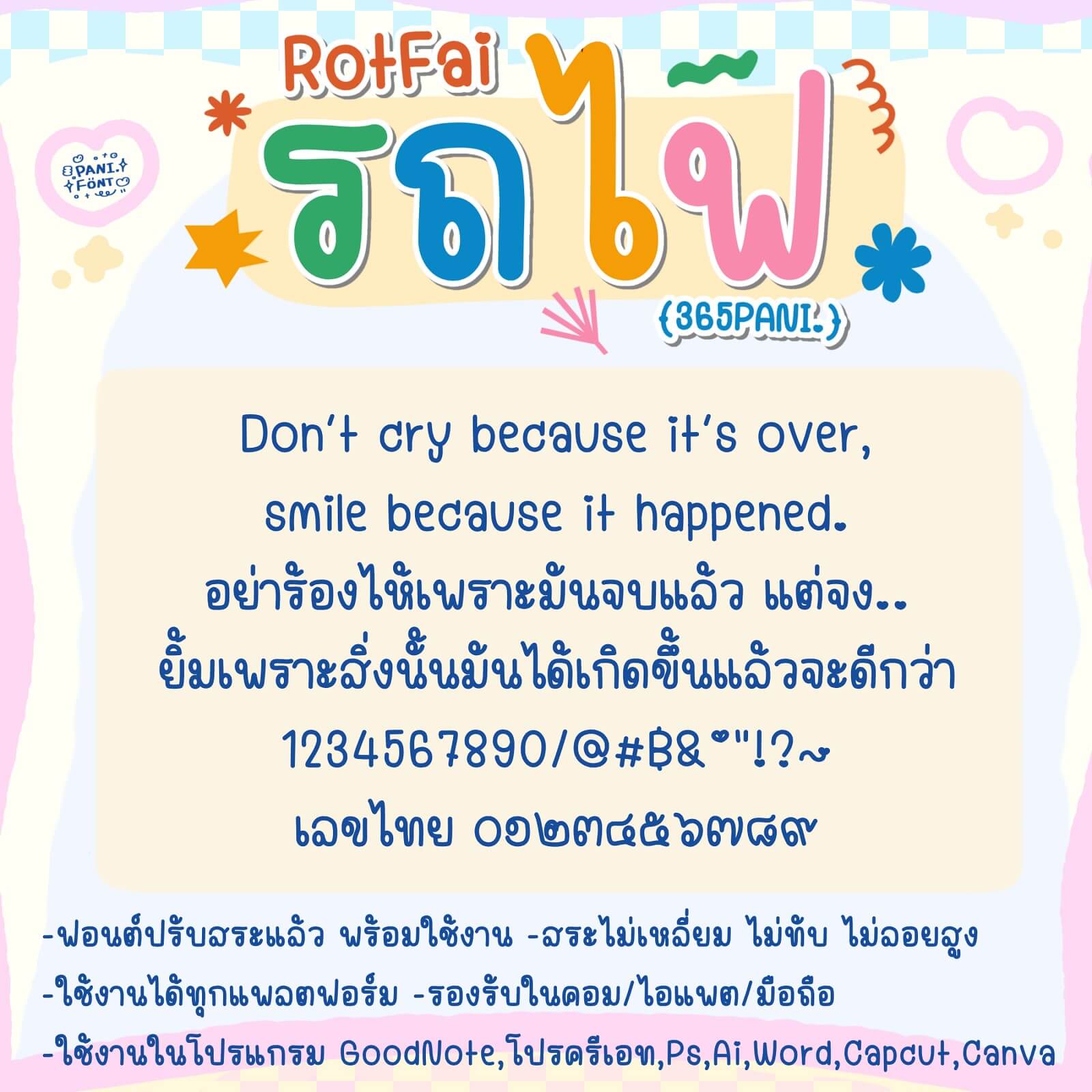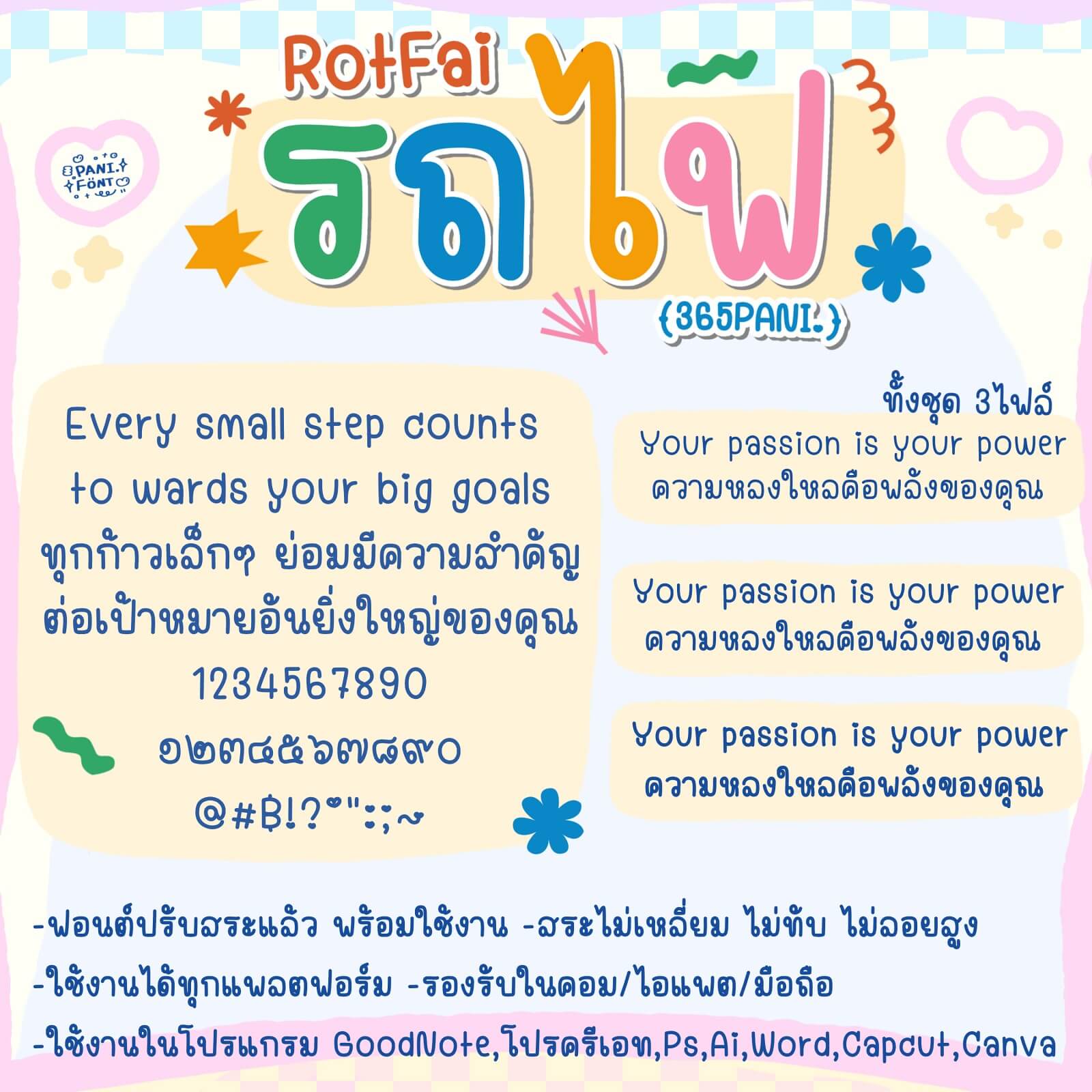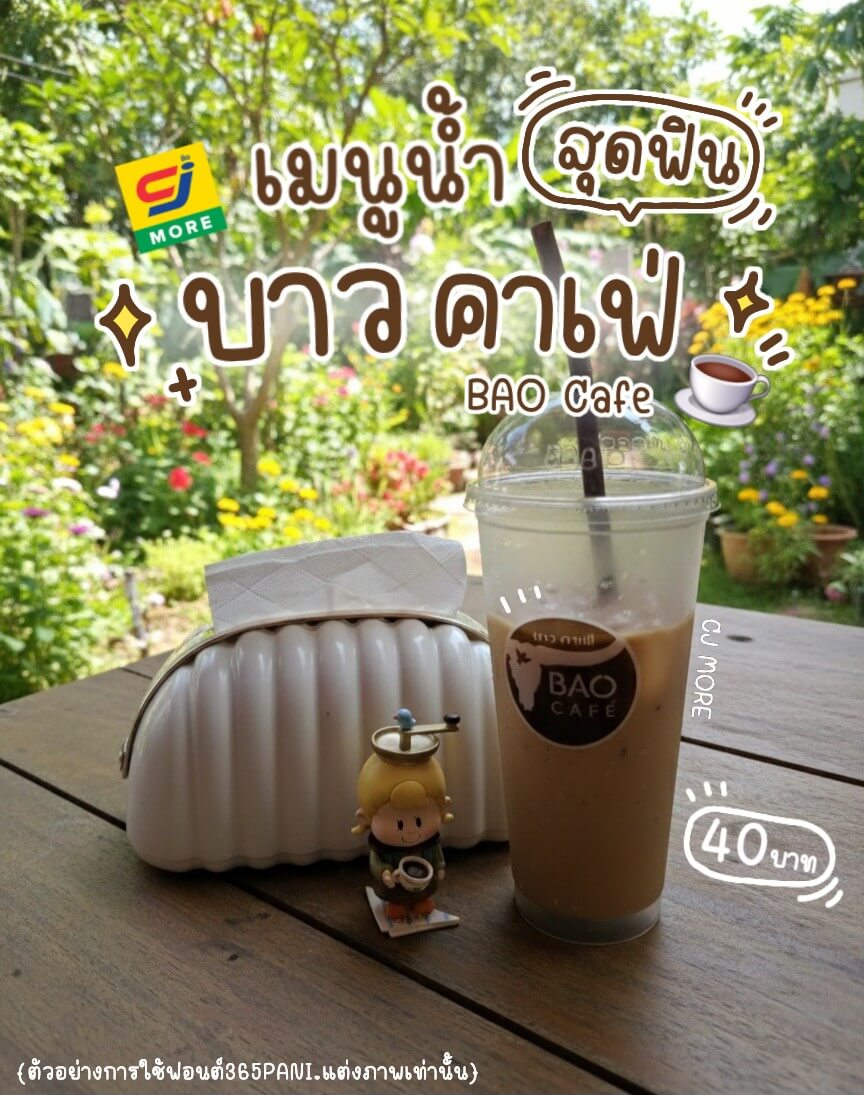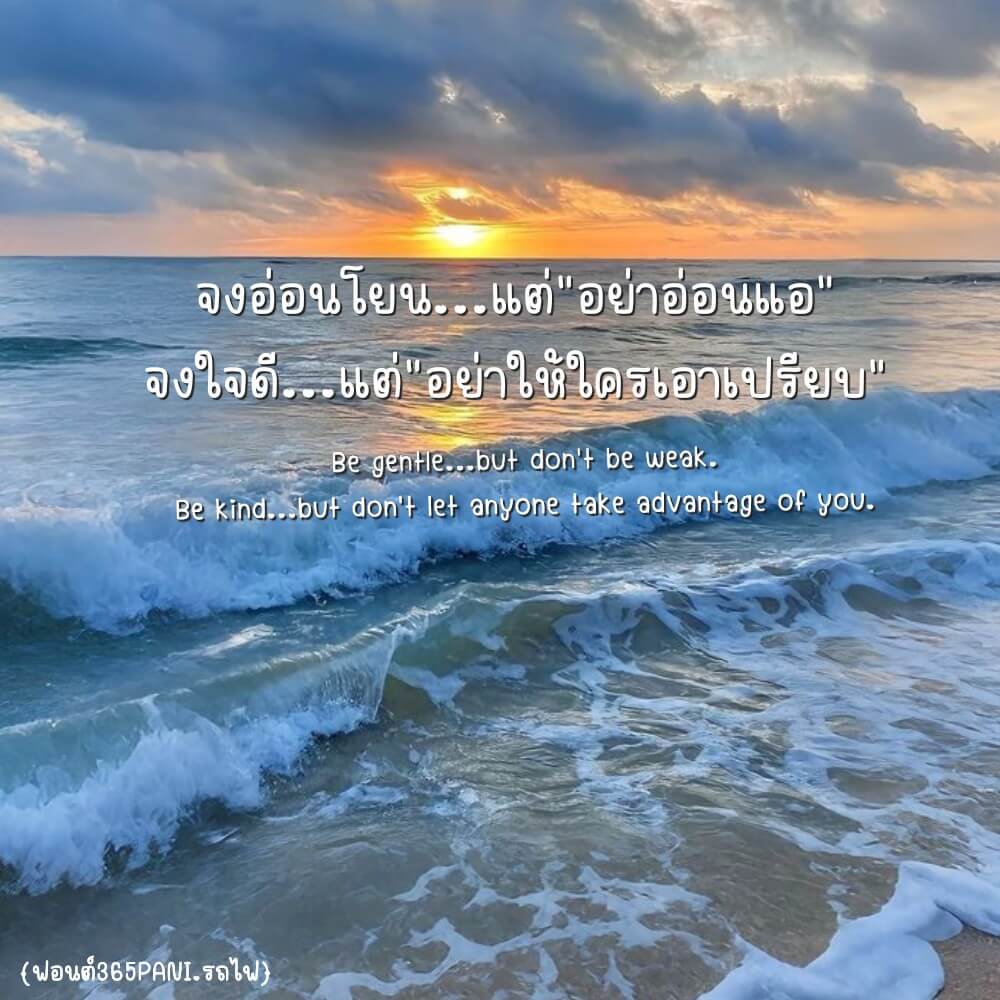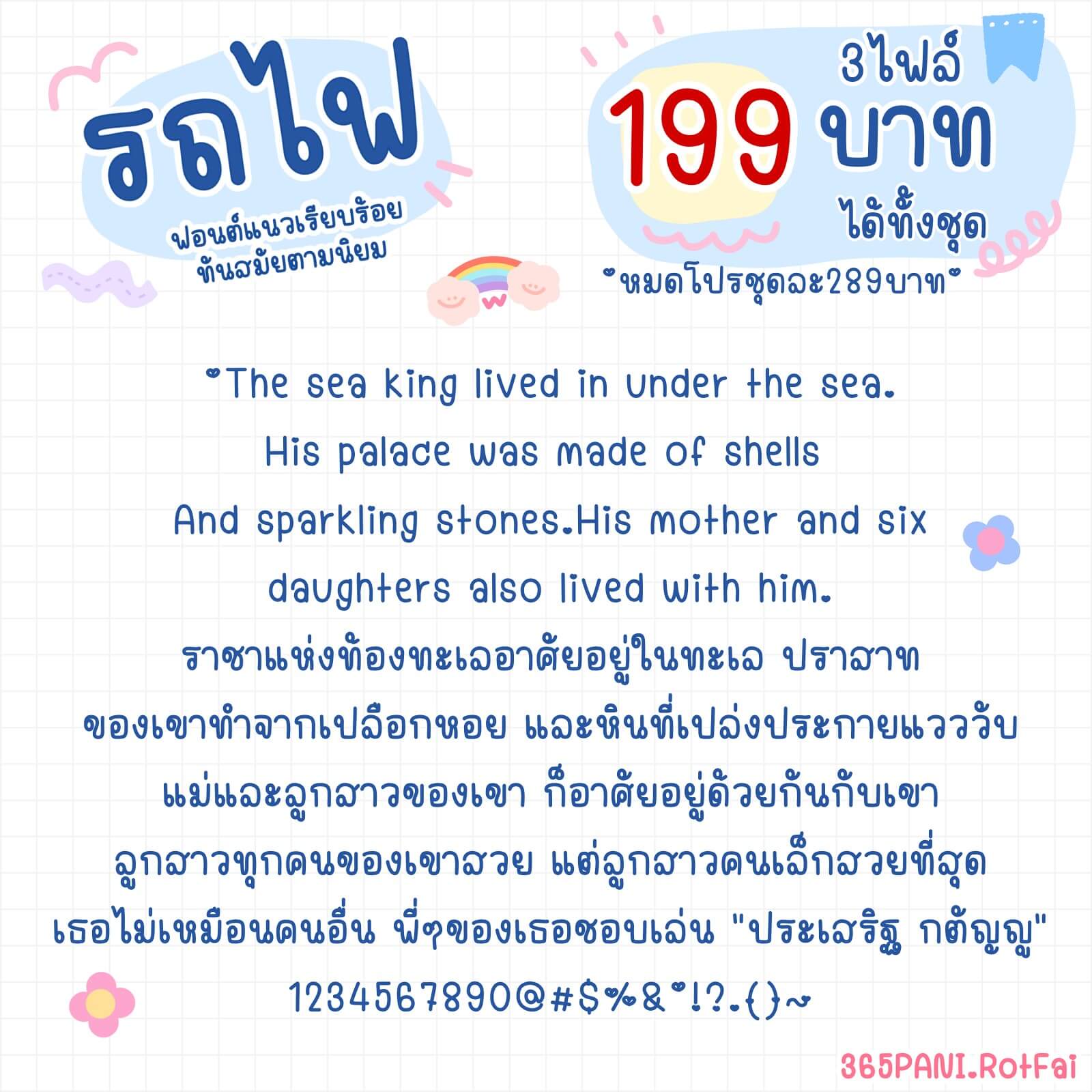
365PANI.รถไฟ
ฟอนต์ 365PANI.รถไฟ – ฟอนต์แนวอ่านง่าย เรียบร้อย ตัวขนาดกำลังดี ใช้แล้วมีความอบอุ่น ชัดเจน เหมาะกับชิ้นงานหลากหลาย จดรายละเอียด ทั้งแต่งภาพ แต่งเปิดคลิป ทำสื่อ ทำใบงาน พรินต์งาน สวย ครบ จบเลยค่ะ^^